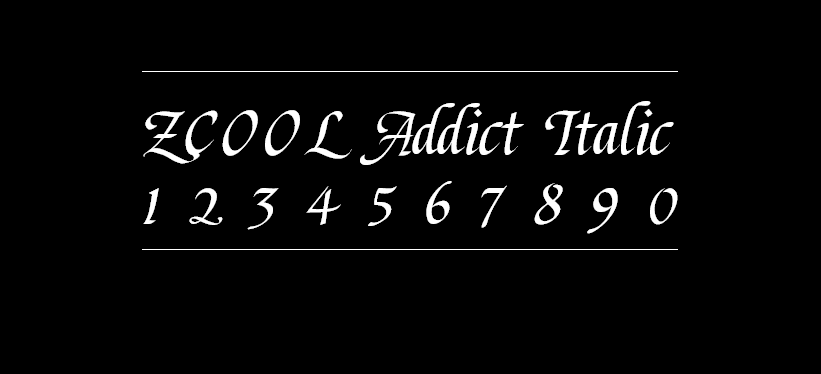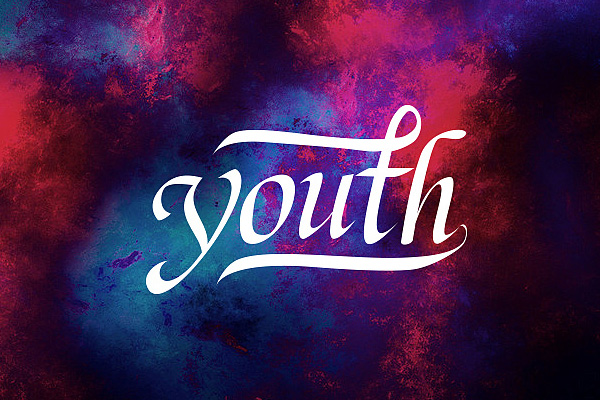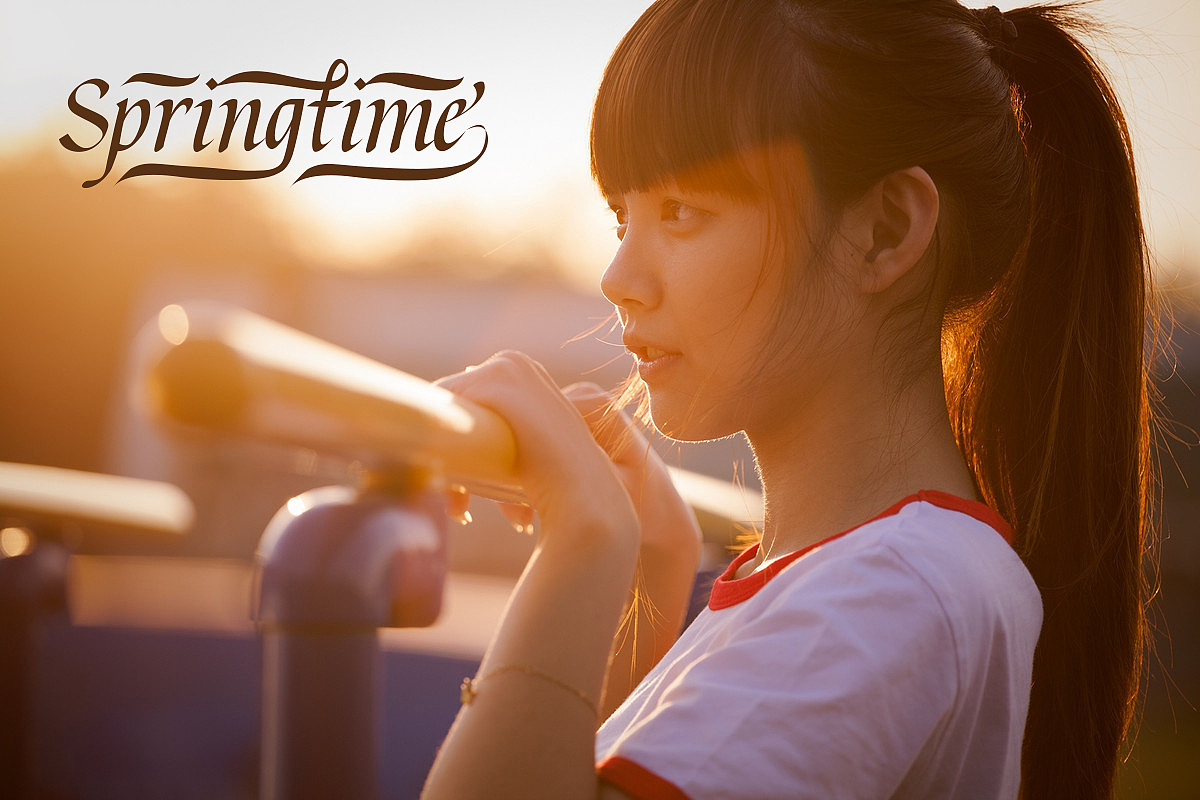
站酷意大利体
站酷意大利体是由大猫Addict设计,并由站酷冠名的首款公益西文字库。这款字体是免费商用的西文字体,适用于各种商业场景和项目。其设计风格独特,具有优美的线条和流畅的外观,能够为文字排版带来更加优雅和精致的效果。站酷意大利体的推出,不仅为设计师和开发者提供了更多的字体选择,同时也为公益事业做出了贡献。这款字体可以被广泛应用于标志、海报、广告、网站等各种设计领域,帮助设计师们更好地呈现创意和设计理念。